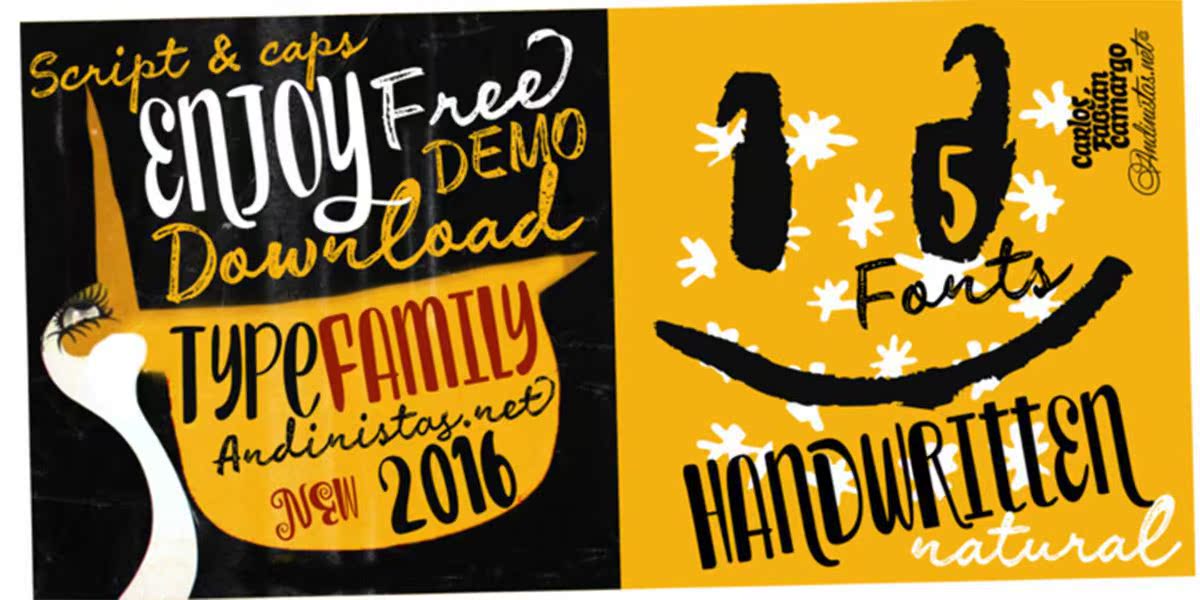
Enjoy Typeface Free Demois是FantFabian Amargo的一部分。它的5个FontSwowking组或独立组。当完成插图或需要有机字体的重大项目时,您将发现以大写、小写和数字形式反映的按需属性,并使用Brush和Fluidink进行书写。这是由于最大的人类协调逻辑,吸引对自助餐厅、植物销售、面包店等感兴趣的平面设计或广告。